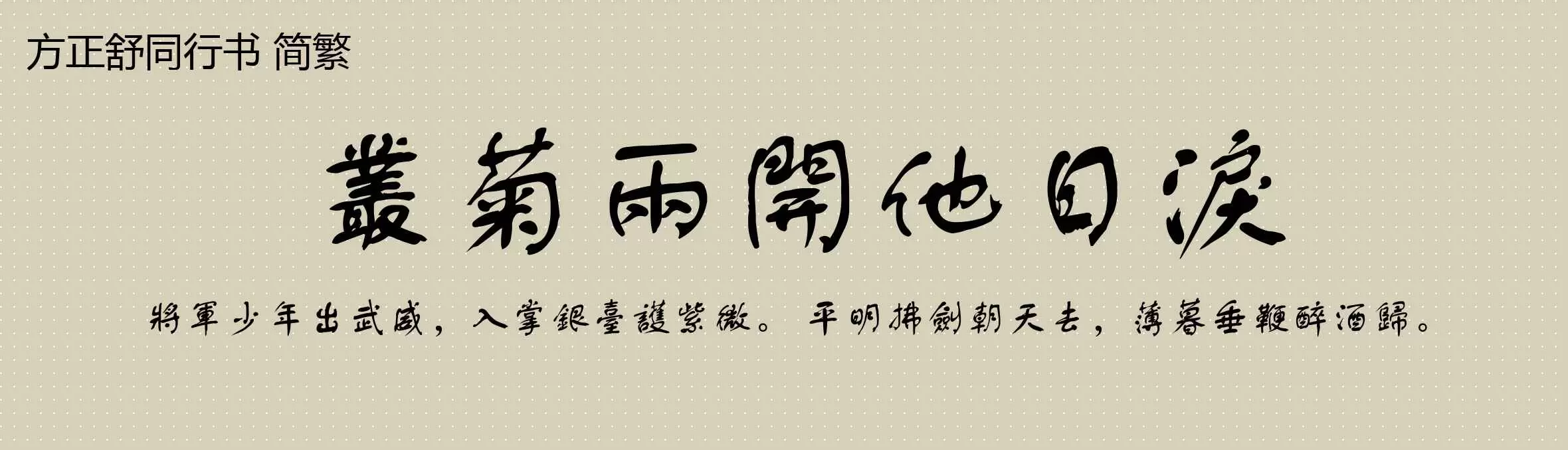
方正舒同行书由舒同先生指定书法家孙志皓先生创作。舒同先生是第一届中国书法家协会主席,毛泽东称他为“党内一支笔”。字形浑厚雄健,笔意舒朗开阔,风格苍劲朴拙。
舒同(1906-1998年)中国书法家。又名宜禄。江西东乡人。1926年加入中国共产党。1930年加入中国工农红军。参加过长征。新中国成立后,历任华东军区政治部主任兼华东军政委员会文教委员会主任、华东人民革命大学校长、中共山东省委第一书记兼济南军区政委、中国人民解放军军事科学院副院长。是中国书法家协会的创始人之一。曾任中国书法家协会第一节主席、第二届名誉主席。其书采粹百家,端庄凝重,疏散飘逸,形成特有的风格,被誉为“舒体”。有《舒同字帖》。